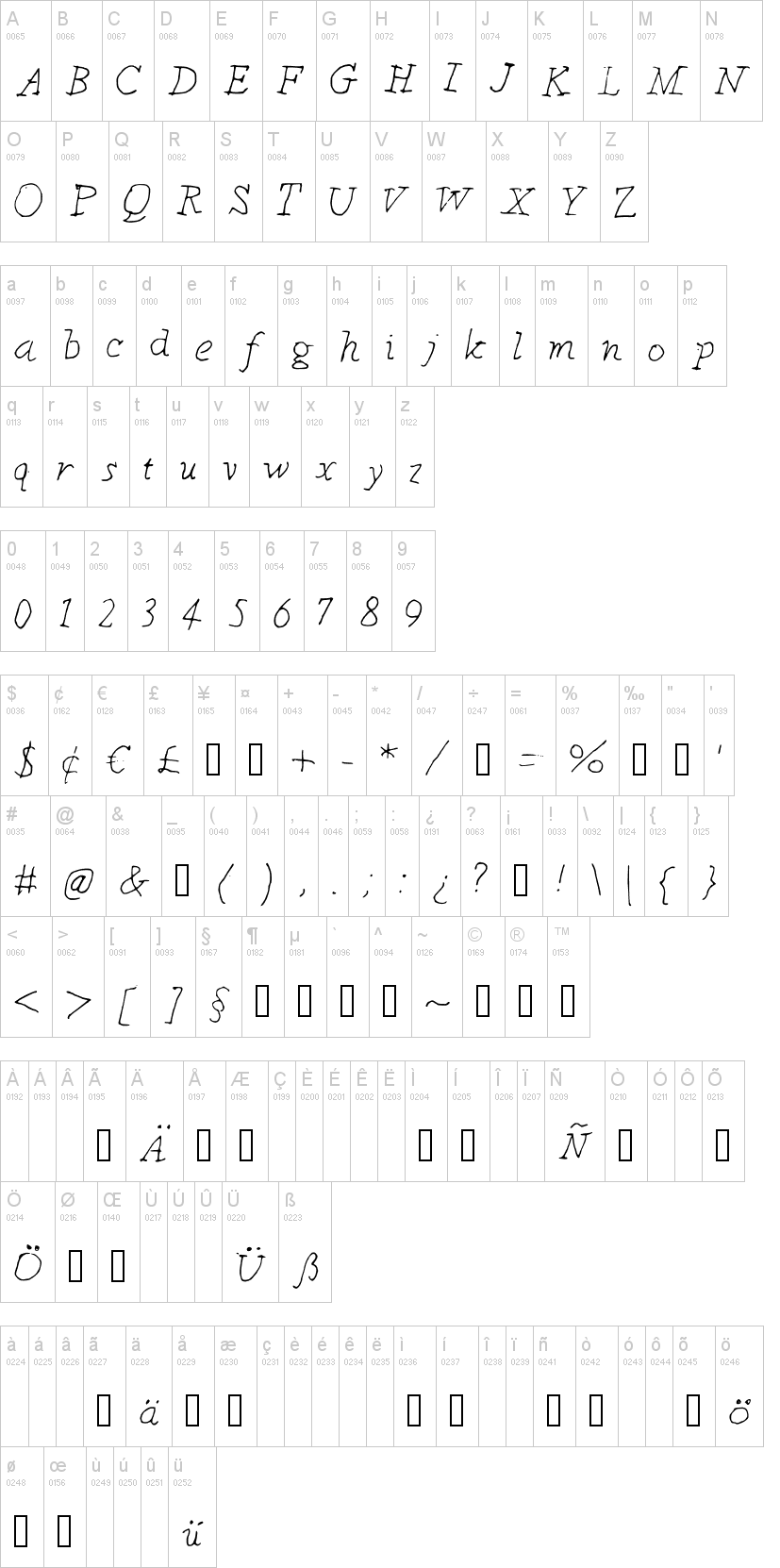
Kindergarten是一款简约的字体,由英国设计师Paul Lloyd设计,于2009年发布。它的特点是简洁、可读性强,有一种简单而又友好的氛围。它的设计灵感来自于孩子们在幼儿园的手写字体,是一种特别的手写字体类型,可以用来创造有趣的文字设计。Kindergarten字体细节丰富,可以用来创造出可爱的、温暖的、有趣的文字设计。内容介绍
Kindergarten是一款非常不错的手写艺术字体,具有很好的视觉感,适合于文化类的宣传设计、商业类品牌的广告和产品包装设计以及个性化文字排版等较多场景。